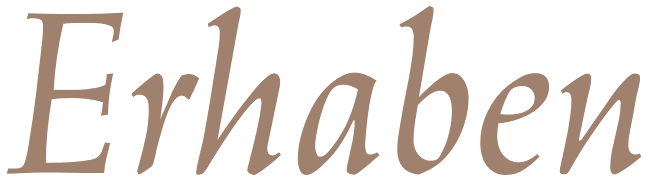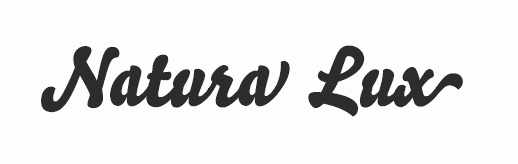
Grazile, edle Schrift gesucht
ich bin momentan auf der Suche nach einer—wie bereits in der Beschreibung steht—grazilen und edlen Schrift.
Die Schrift sollte am besten eine ähnliche Anmut verkörpern, wie z.B. diese Bilder:
Ich habe es zuerst einmal mit den Light-Schnitten der Myriad, Source Sans und Segoe UI versucht.
Die waren mir aber irgendwie zu steril.
Ich hoffe es kommen ein paar Vorschläge zusammen.
Vielleicht mal etwas Ausgefalleneres ausprobieren?
Auch die Disturbance könnte funktionieren. Bei den Serifenlosen könnte ich mir auch eine Gotham Thin vorstellen oder die Whitney in einer Light-Variante.
Bisher hast Du es ja mit den üblichen Verdächtigen versucht und nicht beispielsweise zu der Schrift von Monokrom (Vinter) gegriffen. Möchtest Du ohne extra Kosten vorwärts kommen, lucid?
Hmm, von Narziss bis Neue Haas Grotesk XXThin ist da vieles denkbar. Es kommt eben darauf an, welche Wirkung erzielt werden soll.
Ah, man gut, dass ich alle Antworten gelesen habe - die Narziss hätte ich jetzt auch vorgeschlagen. Sie ist ja mittlerweile fast ein Klassiker für solche Anwendungen.
Danke für die Vorschläge. Die ersten paar sind mir etwas zu klassisch, da fehlt mir das Grazile. So etwas in Richtung Guadalupe könnte ich mir aber vorstellen.
Bisher hast Du es ja mit den üblichen Verdächtigen versucht und nicht beispielsweise zu der Schrift von Monokrom (Vinter) gegriffen. Möchtest Du ohne extra Kosten vorwärts kommen, lucid?
Hmm, von Narziss bis Neue Haas Grotesk XXThin ist da vieles denkbar. Es kommt eben darauf an, welche Wirkung erzielt werden soll.
Wow. Die Narziss gefällt mir wirklich sehr gut :) Und der Designer hat ja noch viele weitere sehr schöne Schriften im Programm. Danke, kannte ich noch gar nicht!
Der italic Schnitt der Hera Big gefällt mir auch sehr gut:
Das Minuskel-e des Narziss Drops-Schnitt gefällt mir durch seine geschwungene Form sehr gut. Und überhaupt gefallen mir die "Tropen".
Mit der Narziss habe ich auf jeden Fall schon eine Schrift, die eigentlich sehr gut passen würde.
Aber vielleicht gibt es noch eine Schrift, die weniger "Didone" ist, also z.B. durchgängig "thin" mit Tropfen oder so...
Weniger Didone mit Tropfen könnte Archer sein - wenn der Preis keine Rolle spielt  :-)
Die Buttermilk und die Tillom gefallen mir auch ganz gut, Danke.
Weniger Didone mit Tropfen könnte Archer sein - wenn der Preis keine Rolle spielt  :-)
Oh ja, die Italic-Schnitte von Archer haben auch was :)
Mir ist noch die Schrift der Inschrift auf dem Ring aus der "Herr der Ringe" eingefallen.
Die hat so elegante lange Ober- und Unterlängen. Gibts da vielleicht so was ähnliches?
Hab gerade auch noch das hier gefunden:
Die Headline-Schrift ist wirklich sehr schön, kennt die jemand?
Hab gerade auch noch das hier gefunden:
Die Headline-Schrift ist wirklich sehr schön, kennt die jemand?
Im Projekttext steht:
new weights of our typeface calendas –a more refined version for text, bold italic, display and swashes– exclusively for the redesign of the town&country magazine by edward leida.
Eine frühere Version der Calendas gibt es hier zum freien Download.
Die Headline-Schrift ist wirklich sehr schön, kennt die jemand?
"Calendas Display" heißt sie. Und StefanB war schneller :-)
Die Buttermilk und die Tillom gefallen mir auch ganz gut, Danke.
Oh ja, die Italic-Schnitte von Archer haben auch was :)
Mir ist noch die Schrift der Inschrift auf dem Ring aus der "Herr der Ringe" eingefallen.
Die hat so elegante lange Ober- und Unterlängen. Gibts da vielleicht so was ähnliches?
Nach dem, was Dich bisher so angesprochen hat lucid, könnte evtl. auch noch die Bodebeck von Linotype passen (wenn Swashes kein Muss sind): http://www.fontshop.com/fonts/family/bodebeck/?device=fb_iphone_app_v3.0&affid=108000
Des Weiteren bin ich noch über die Sangbleu gestolpert: http://www.fontshop.com/fonts/family/sangbleu_sans/?device=fb_iphone_app_v3.0&affid=108000